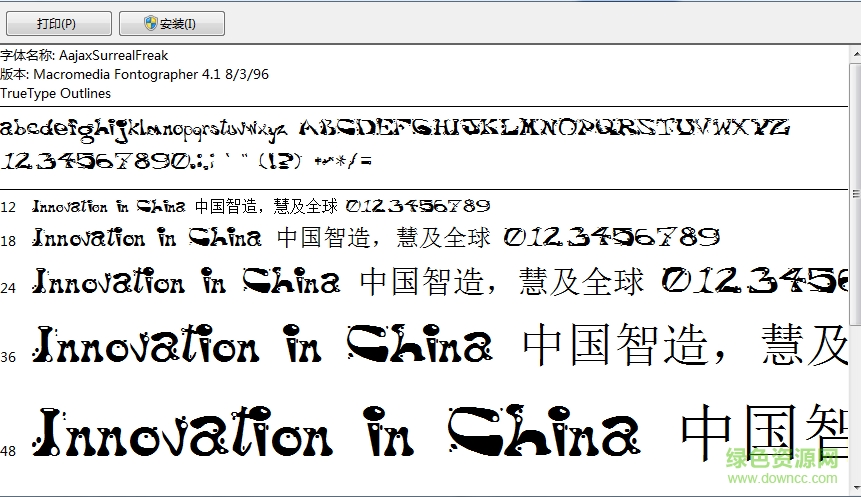
aa鬼泣字體
aa鬼泣字體是一款專為電腦用戶準(zhǔn)備的可愛型電腦字體,字體干凈,筆畫隨意又不失規(guī)矩,活潑好看,需要的小伙伴快來綠色資源網(wǎng)下載使用吧!
aa鬼泣字體是一款非常有特色的字體,該字體筆形富于變化,浪漫而又溫馨,印刷效果清晰明快,可用于文章、報(bào)紙、書籍廣告制作、裝飾裝幀等!